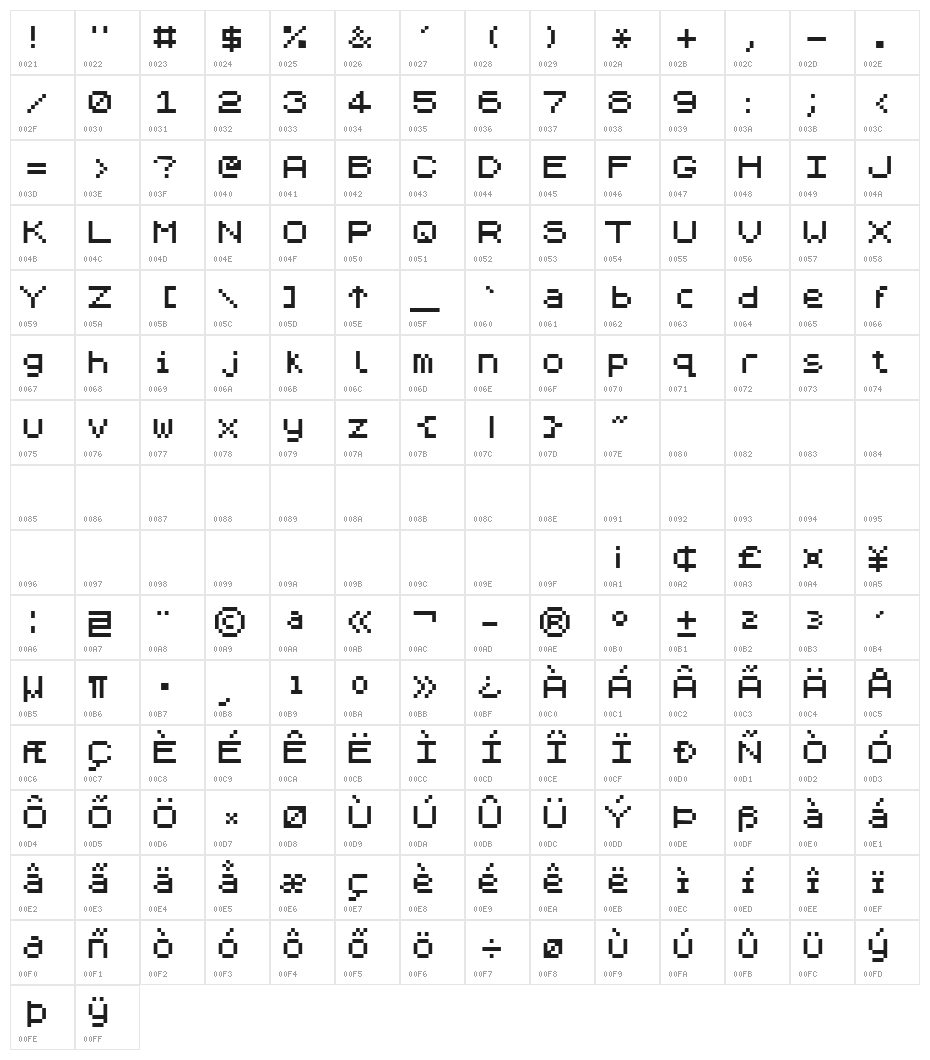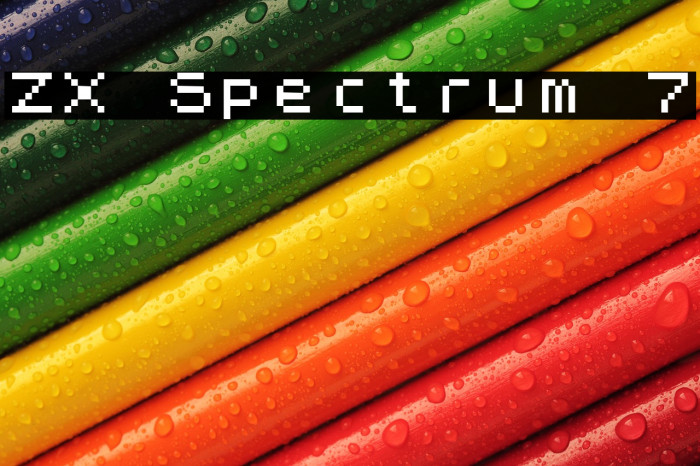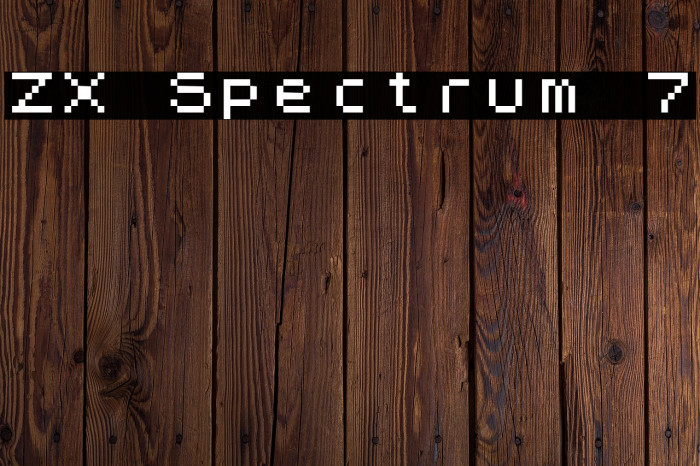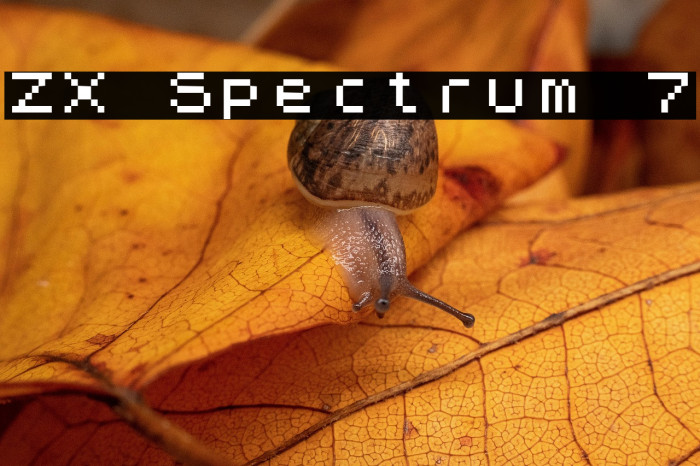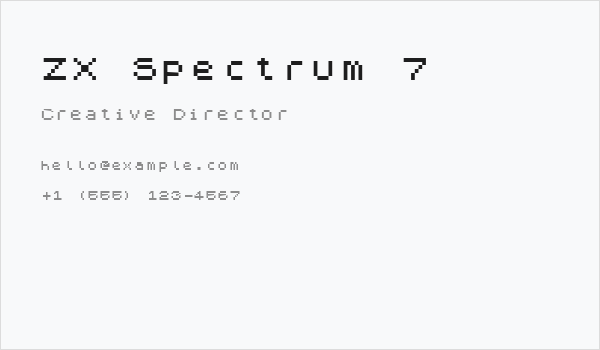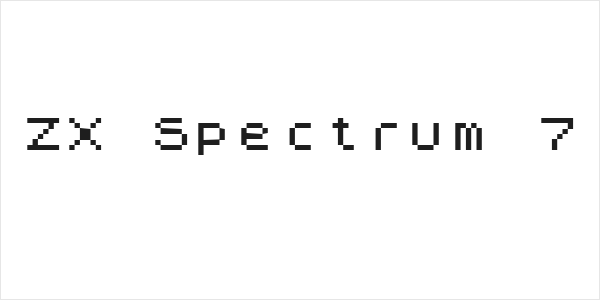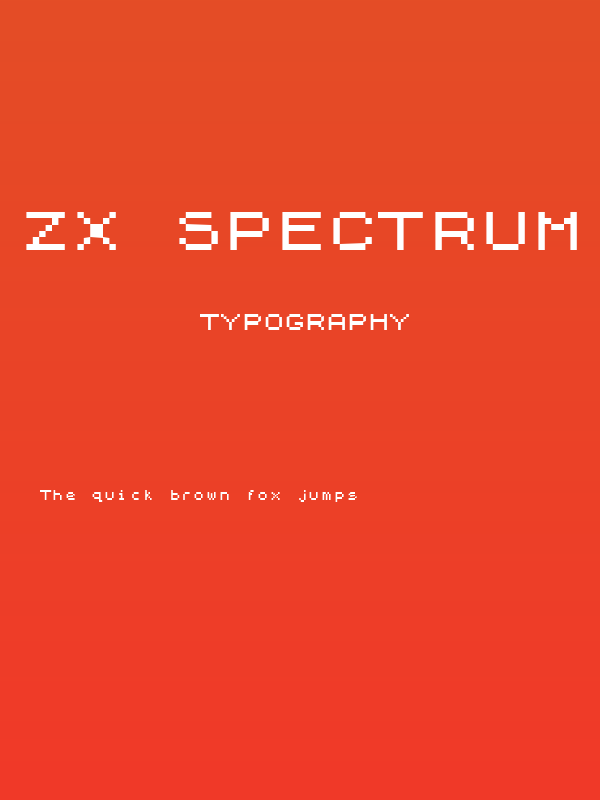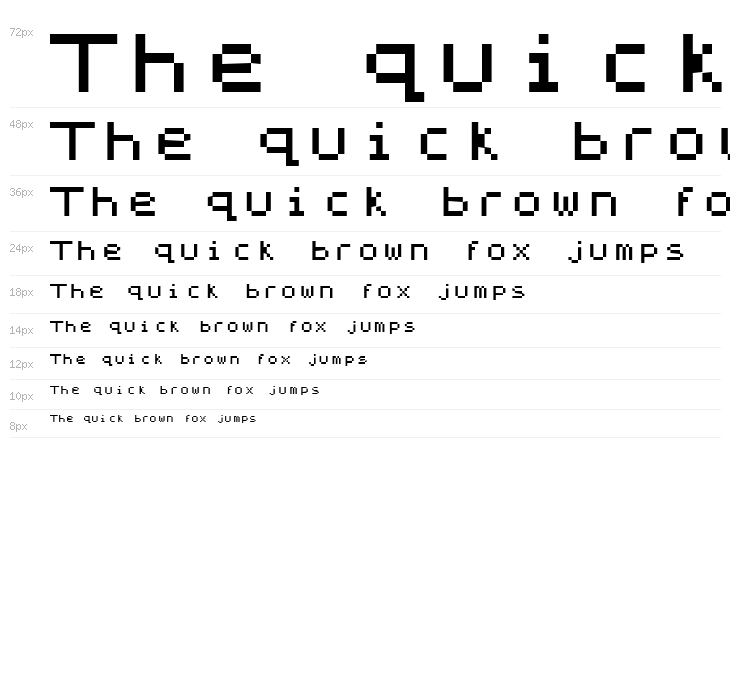
ZX Spectrum 7 Font
| Caso d'uso | Headlines, Logos, Digital displays |
| Progetti proposti | Ideal for retro video games, digital art projects, coding environments, and any design work that seeks to evoke a sense of nostalgia for early computing. |